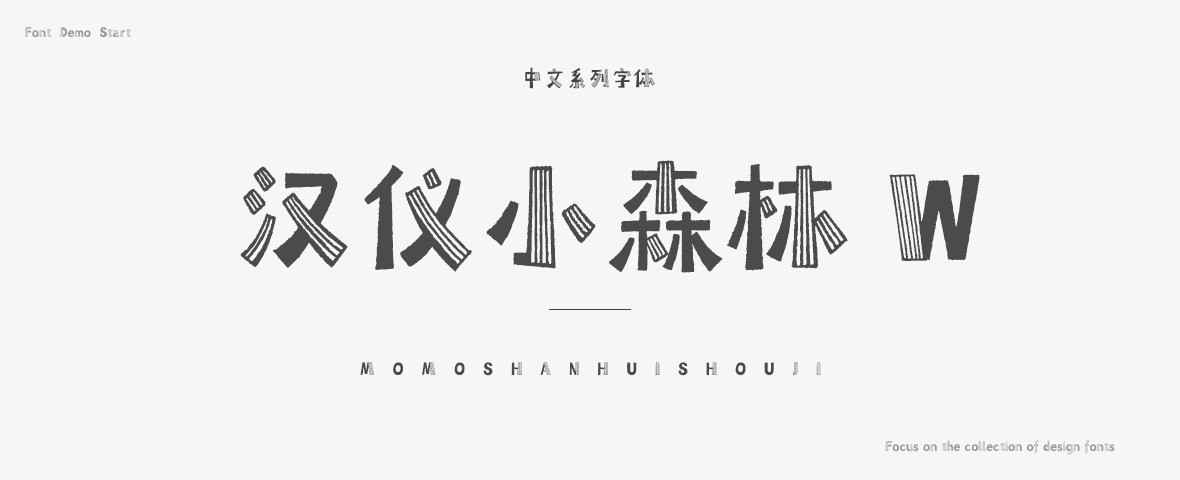
汉仪小森林 W字体
简介:汉仪小森林 W字体是一款手绘风格字体,该字体散发出清新惬意的气息,如同漫步在童话般的森林中,雾霭出散,初夏的晨光映照下来,透过落满雨露枝桠,漫射在湿润的泥土上,焕发出沁人心脾的清香。该字体适合作为标题字,用在玩具礼品、文创周边、产品包装、综艺海报等场合。本次下载仅限个人试用,任何商业使用均需通过汉仪字库书面授权,需要获得版权许可请到汉仪字库官网购买。